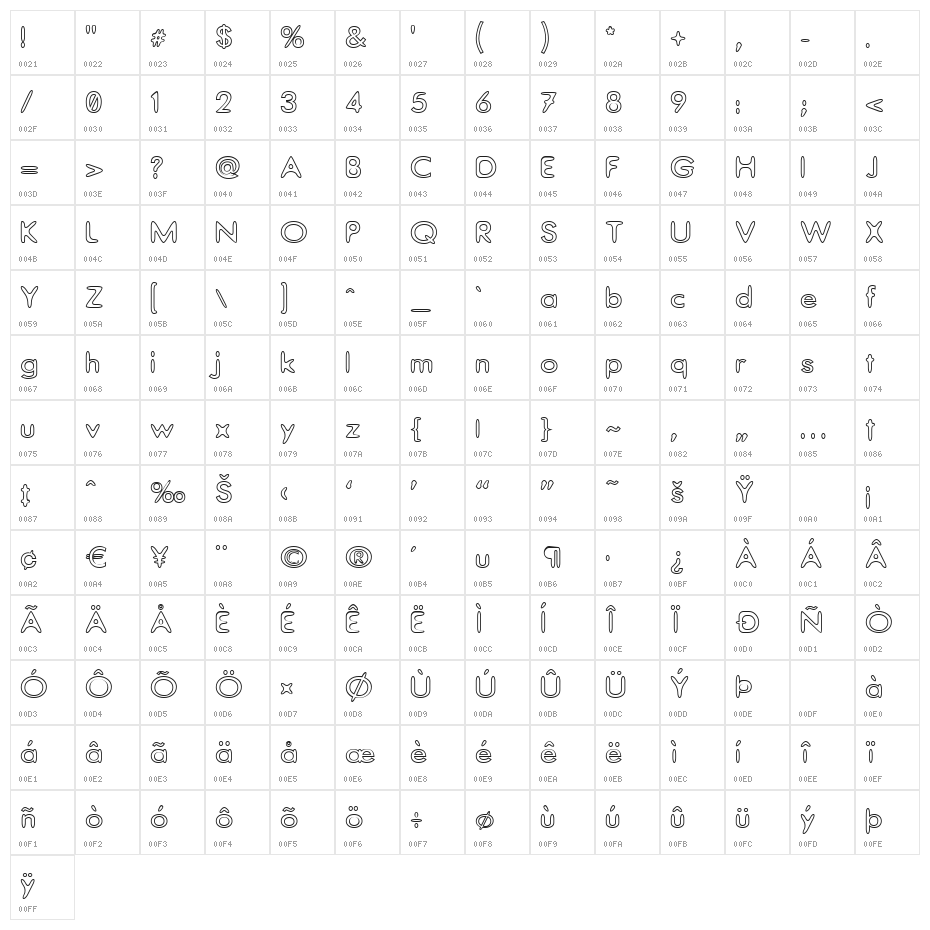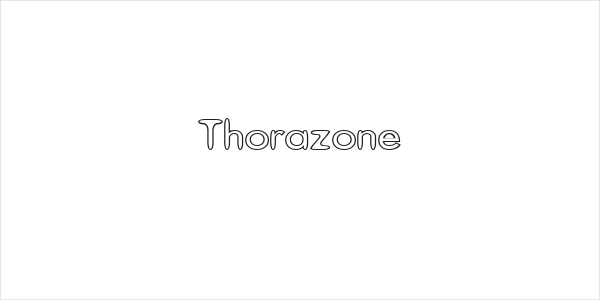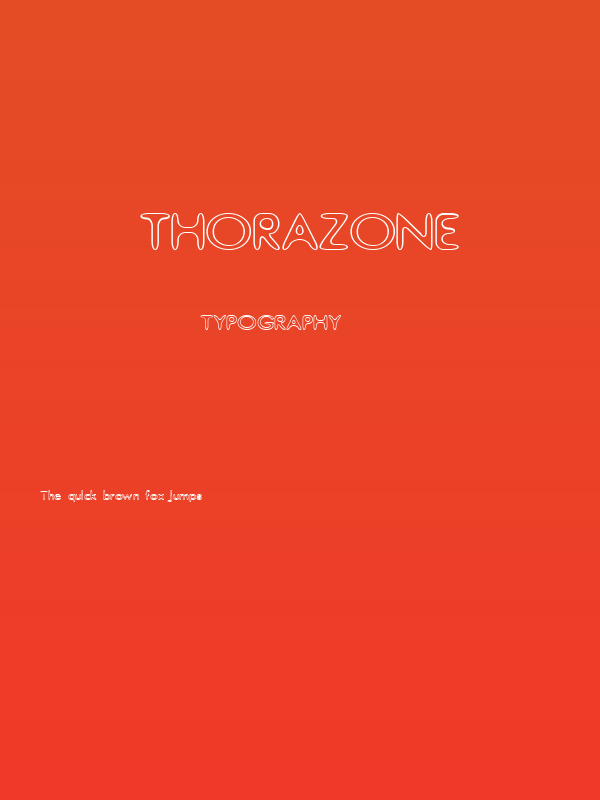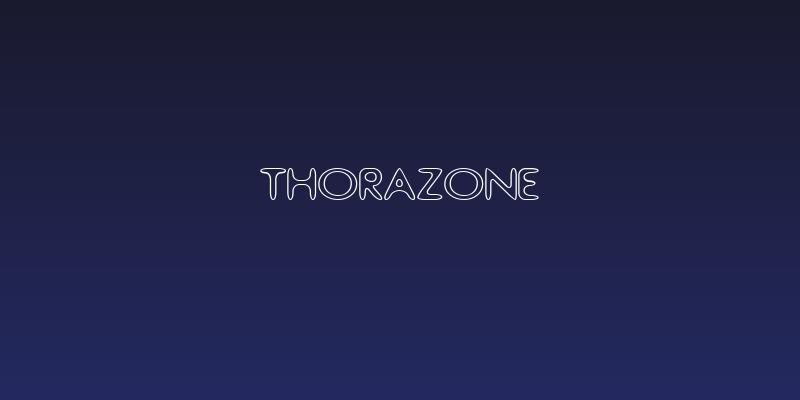
Thorazone Font
| النمط العام | Playful, Creative |
| مشاريع مقترحة | Ideal for children's book covers, playful branding, party invitations, and creative posters. |